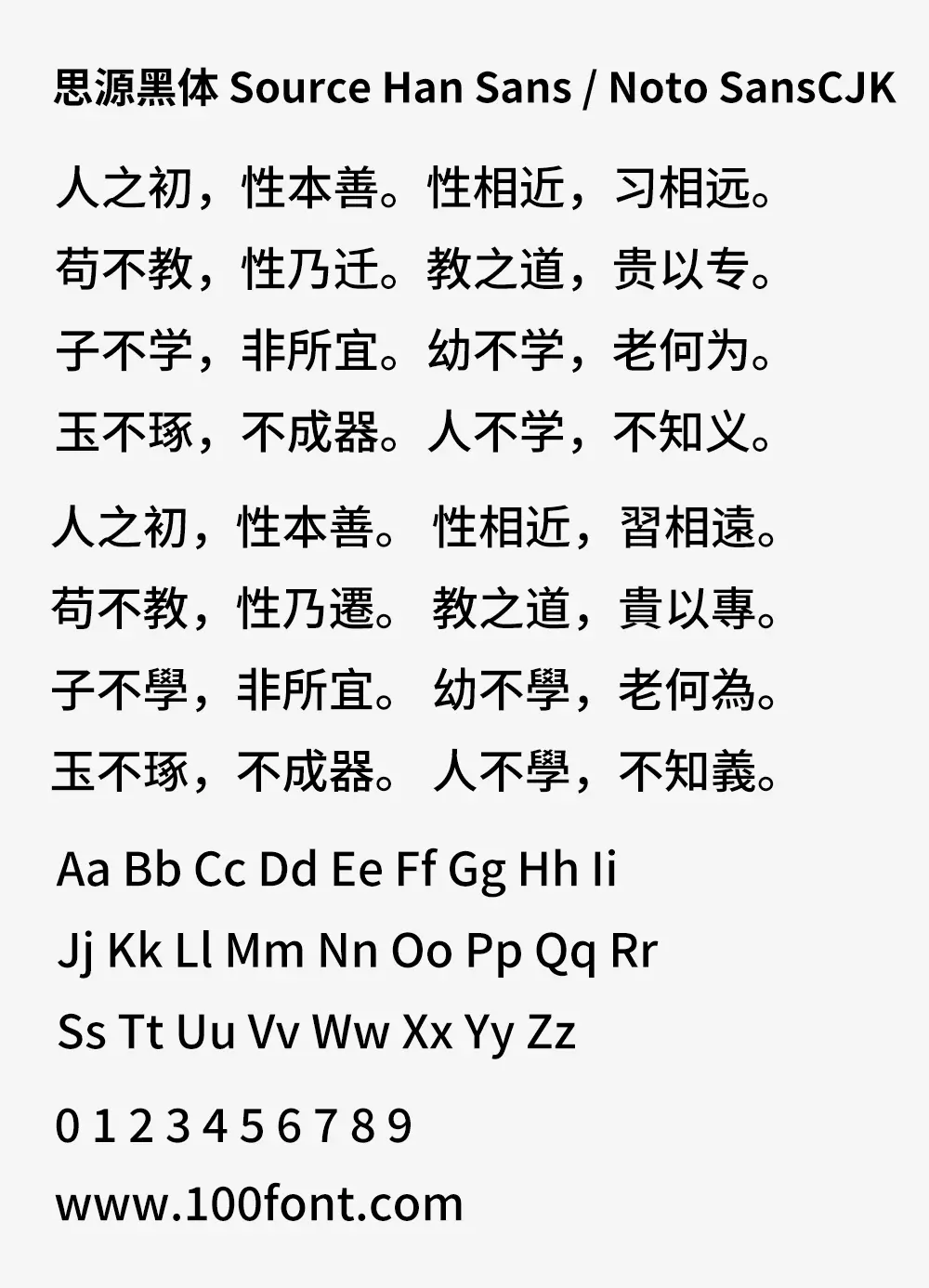
思源黑體是Adobe與Google歷時三年在2014年7月宣佈推出的一款開源字體,這是一款新的供桌面使用的開源 Pan-CJK 字體家族,完全支持繁體中文、簡體中文、日文和韓文,它還包括來自我們頗受歡迎的 Source Sans字體家族的拉丁文、希臘文和西里爾文字形。
該款字體是由Google和Adobe合作開發的,Google將其命名為Noto SansCJK,作為Google的Noto字體家族的成員。Adobe則命名為Source Han Sans,作為Adobe的Source字體家族的一員。Adobe擁有字體設計的版權。發佈的字體文件則可以不受限制的免費使用。
思源黑體通過開源方式提供,數量、開發規模和價值之大堪稱史上之最,已成為需要支持多種語言的字體的設計人員、開發人員和普通用戶的零成本解決方案 。
FAQ1:Adobe和谷歌版的思源黑體的甚麼不同?
思源黑體有兩個版本,一個是Adobe發佈的版本,一個是谷歌發佈的版本,本質上就是一個字體系列,然後各自針對自己的使用場景做了一些特調,最後各自發行了針對自己行業的發行版本而已。
Adobe版本在PS中顯示的字體名稱是“思源黑體”,字重名稱是:ExtraLight、Light、Normal、Regular、Medium、Bold 、Heavy。
而谷歌版本在PS中顯示的字體名稱是“Noto Sans CJK”,字重名稱是:Thin、Light、DemiLight、Regular、Medium、Bold、Black。
思源黑體全面支持了繁體中文、簡體中文、日文和韓文,併兼顧了對四種語言的不同書寫慣例的支持。思源黑體的風格介於現代和傳統之間。設計目標是可以廣泛用於多種用途的計算機字體,比如用於手機、平板、或者桌面的用戶界面、網頁瀏覽或者電子書閱讀等等。